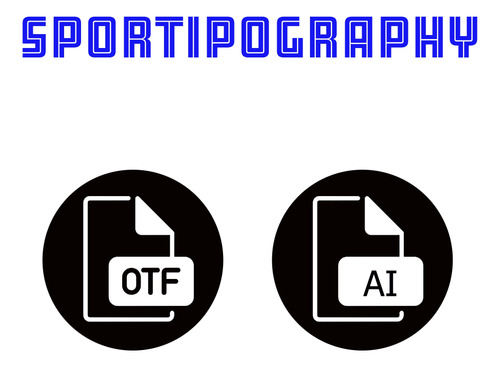
|||| TIPOGRAFÍA TIGRES 2025-2026 ADIDA s ||||
¡Caracteres alfanuméricos perfectos para tus diseños!
Con diseño liso ideal para números frontales y shorts.